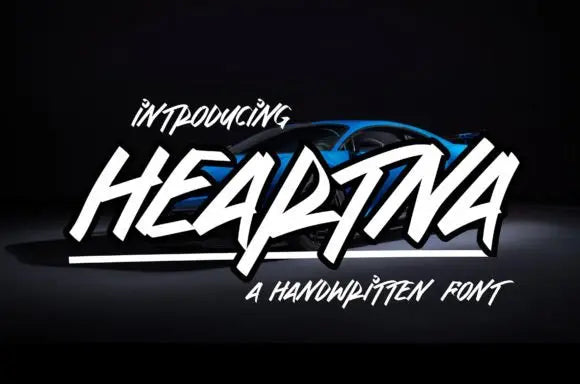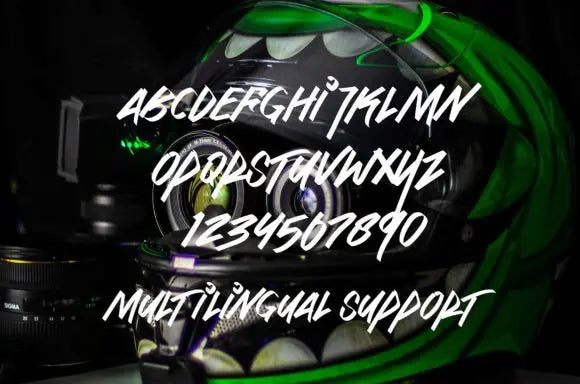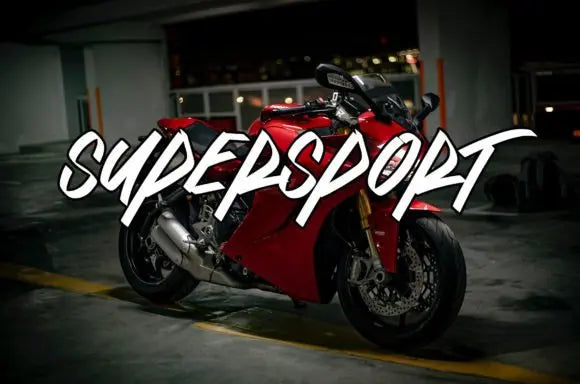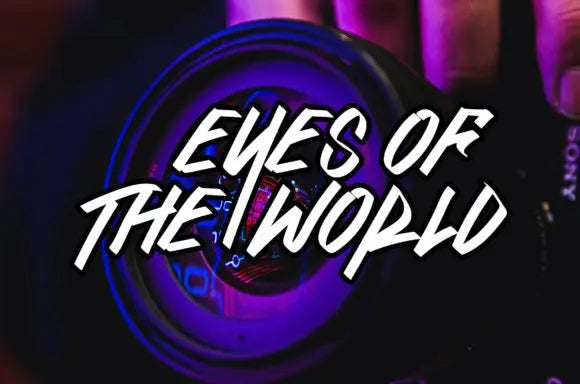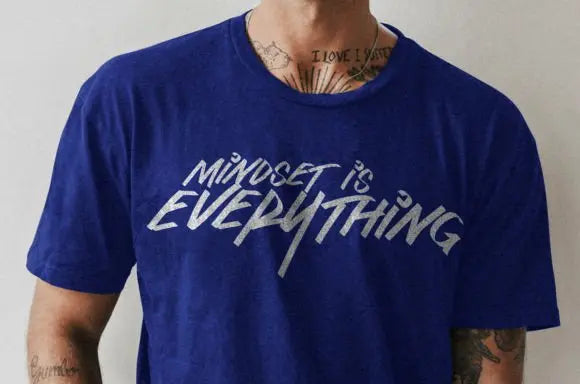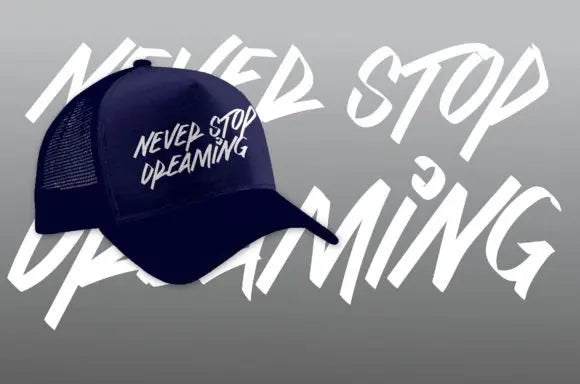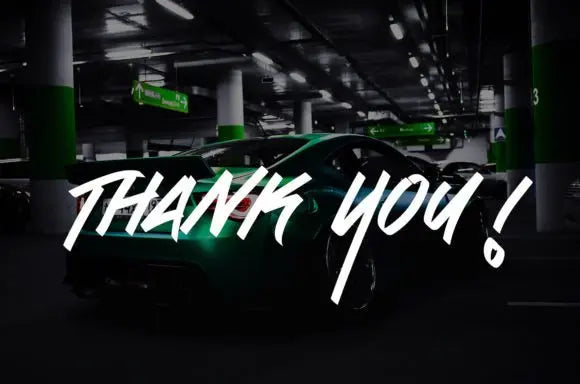
Fuente Heartna
Heartna es una fuente manuscrita atrevida y asertiva. ¡Diseñada magistralmente para convertirse en una verdadera favorita, esta fuente tiene el potencial de llevar cada una de tus ideas creativas al más alto nivel! Diseñada para lograr el máximo impacto, Heartna Font es una opción inigualable para cualquier proyecto de diseño.
Sus trazos atrevidos y asertivos y su impecable estilo manuscrito elevan el potencial de todas y cada una de las ideas creativas.